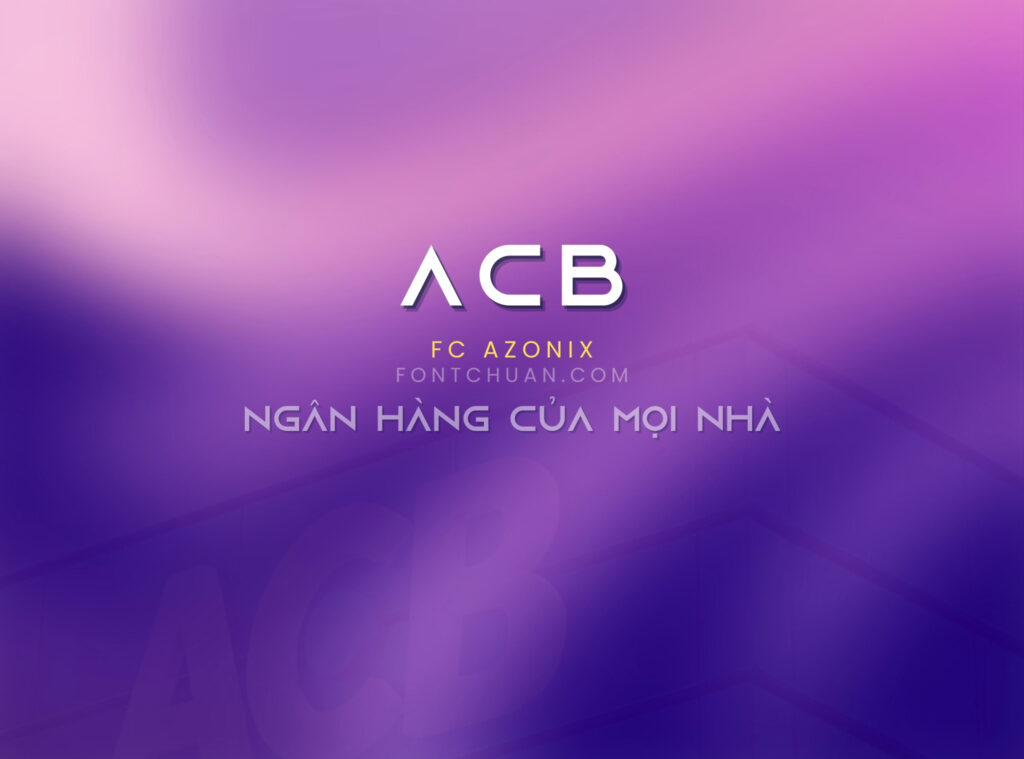
Azonix là một font chữ sans-serif hiện đại, được thiết kế bởi Mixo FX và phát hành vào khoảng năm 2018. Với thiết kế hình học đậm nét, Azonix mang lại cảm giác mạnh mẽ và tối giản. Font này bao gồm các ký tự in hoa, chữ số và các ký hiệu, tạo sự đa dạng trong việc sử dụng. Bên cạnh các ứng dụng chuyên nghiệp, Azonix cũng có thể được sử dụng như một Font Lễ hội để trang trí các ấn phẩm sự kiện, poster hay banner vui tươi, đồng thời phù hợp làm font ngày nhà giáo Việt Nam cho các thiệp mừng, poster và banner chúc mừng thầy cô.
Để hỗ trợ miễn phí cho người dùng Font Chuẩn đã cho ra đời phiên bản FC Azonix thế hệ mới và chia sẻ free, đảm bảo hiển thị chính xác các ký tự tiếng Việt. Ngoài ra, font này còn hỗ trợ tiếng Anh và nhiều ngôn ngữ Latin khác, mở rộng khả năng ứng dụng trong các dự án quốc tế, đáp ứng nhu cầu đa dạng của bạn đọc và hỗ trợ ứng dụng thực tế trong các dự án thiết kế.
Với cấu trúc chữ vừa phải, các đường nét gọn gàng và thiết kế tinh tế, Azonix phù hợp cho các thiết kế yêu cầu sự hiện đại và chuyên nghiệp. Phù hợp cho các dự án thiết kế như logo, tiêu đề, thương hiệu và các ấn phẩm quảng cáo khác. Đặc biệt, font này thích hợp cho các ngành nghề như quảng cáo, thiết kế thương hiệu và lĩnh vực truyền thông, hoặc có thể sử dụng làm font chữ Tết để tạo nên những ấn phẩm mùa lễ hội vừa hiện đại, vừa rực rỡ không khí Tết.